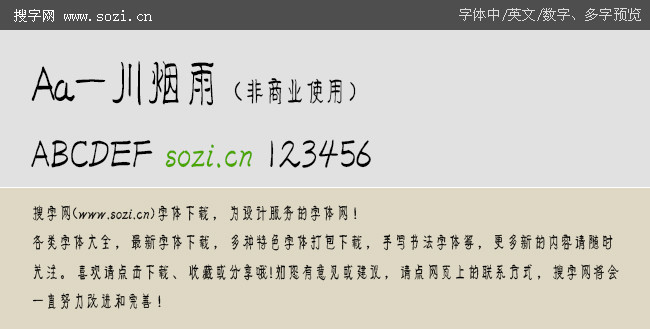
Aa一川煙雨(非商業(yè)使用)
搜字網(wǎng)給大家提供一款A(yù)a一川煙雨(非商業(yè)使用)中文字體下載,該字體是一款手寫(xiě)中文字體,字體筆觸較為纖細(xì),字形端正,具有很好的視覺(jué)感,適合包裝設(shè)計(jì)、書(shū)裝設(shè)計(jì)、海報(bào)設(shè)計(jì)等應(yīng)用(此字體為個(gè)人非商用版,商用可以聯(lián)系QQ:1006760504)。